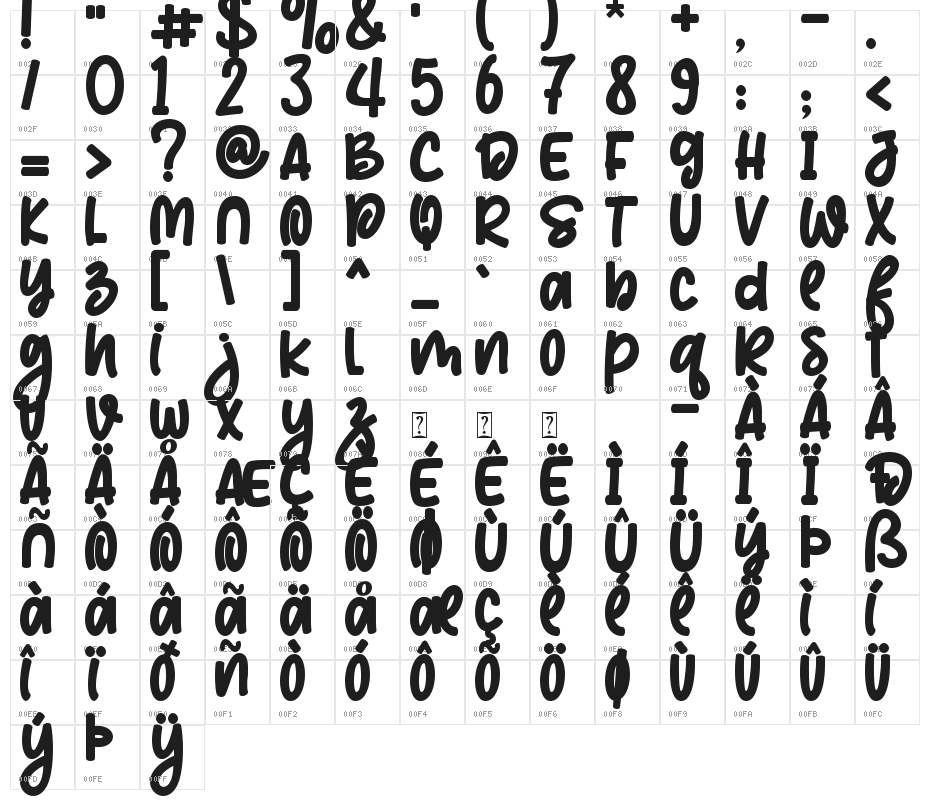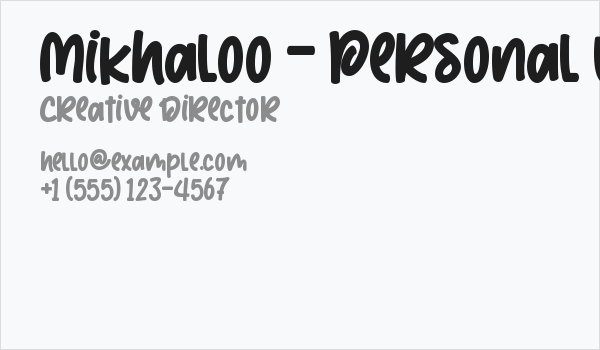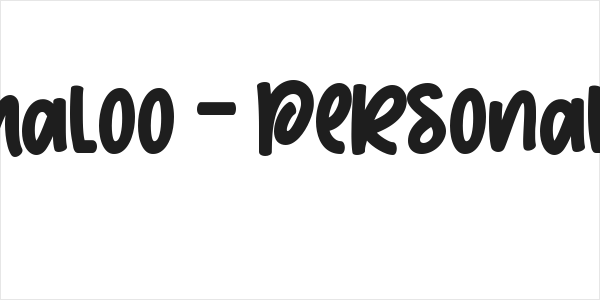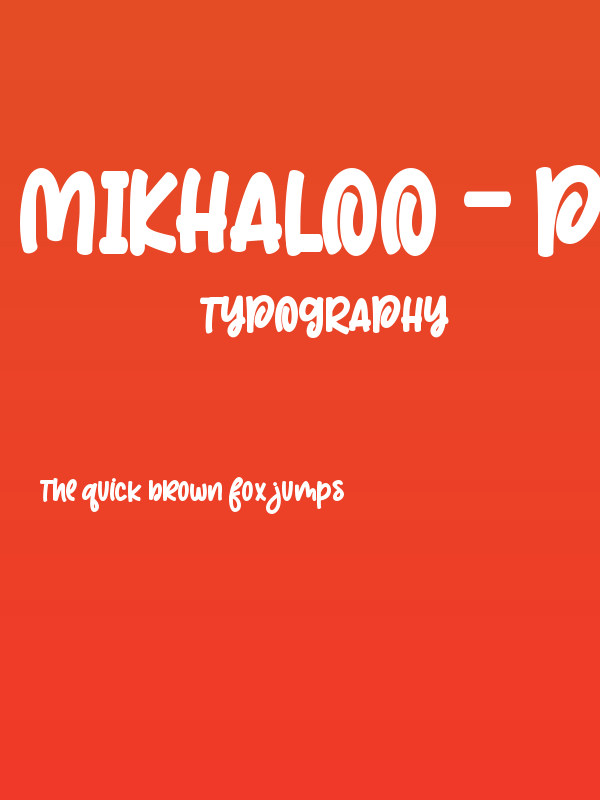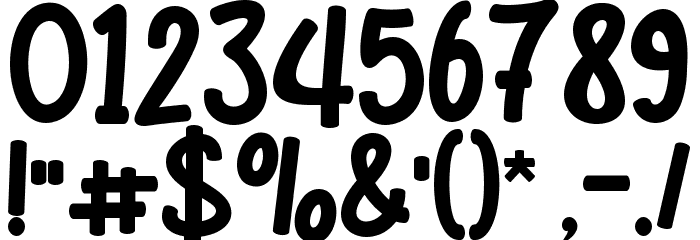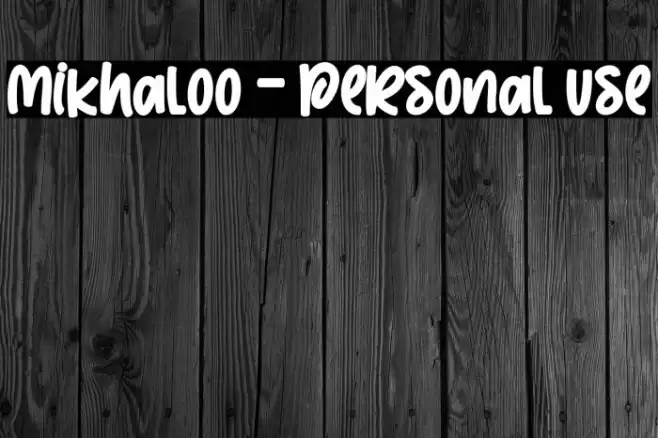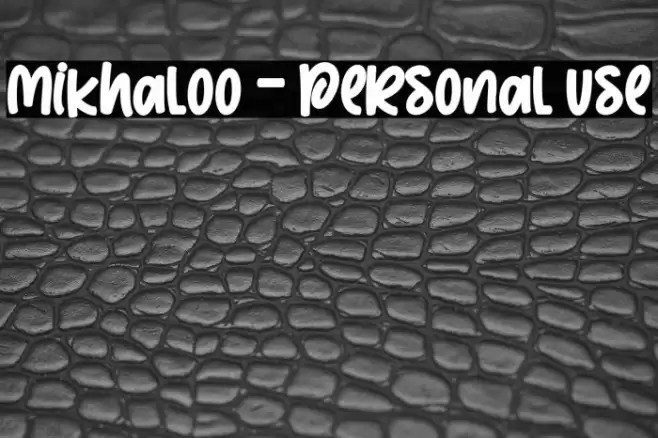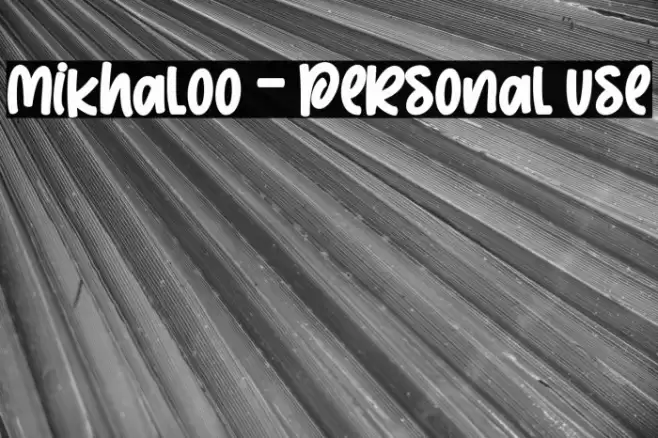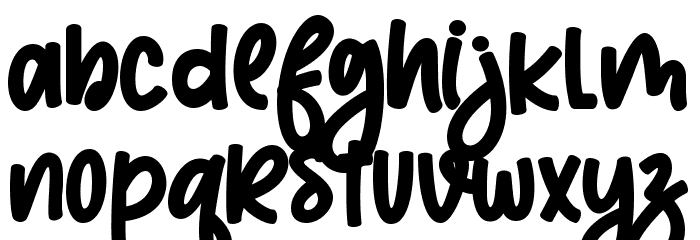
Mikhaloo - Personal use Font
| Gesamtstil | Playful, Decorative |
| Anwendungsfall | Headlines, Logos, Invitations |
| Vorgeschlagene Projekte | Ideal for invitations, greeting cards, children's book covers, and playful branding projects. |